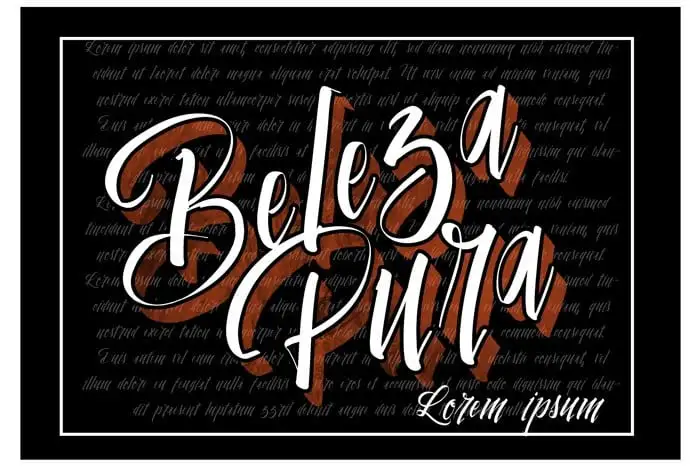
Vtks Beleza Pura Script Font – Download Grátis
A Vtks Beleza Pura Script Font é uma elegante fonte feita à mão para designers que buscam capturar a essência do bom gosto e da autenticidade. Essa escolha de letra, cuidadosamente criada pela equipe na 99designs, une o encanto da antiguidade ao estilo perfeito dos xamanismos escritos por mãos humanas. Com seu estilo clássico inigualável, essa fonte mantém a sensação amigável e confortável que você busca em cada projeto. Indicada para uma variedade de aplicações, desde logos e convites até designs para casamentos, postagens nas redes sociais, anúncios e embalagens de produtos, Vtks Beleza Pura Script é a fonte perfeita para capturar o brilho especial que cada projeto merece.